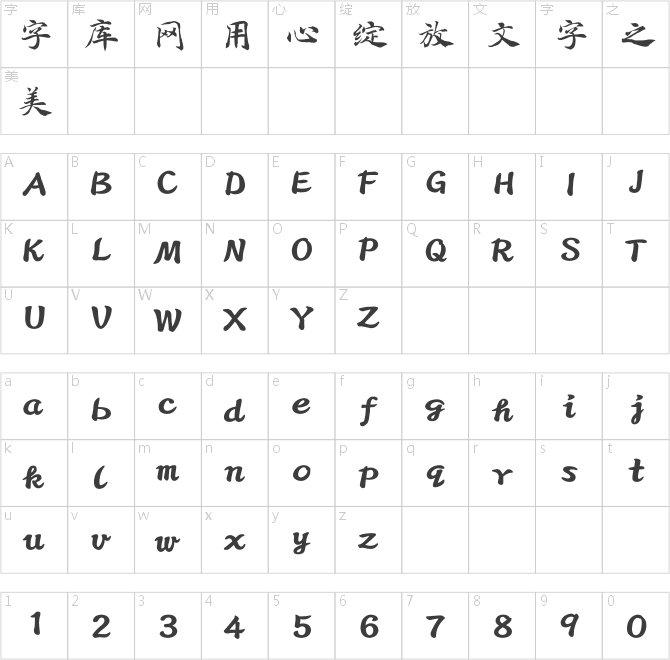
方正字跡-天華褚體 詳情頁(yè)
字體名稱: 方正字跡-天華
方正字跡-天華褚體
方正字跡-天華褚體字體字庫(kù)是一款讓人賞心悅目、百看不厭的中文字體,適合各類廣告和產(chǎn)品包裝設(shè)計(jì)應(yīng)用,字體大小17.59MB,格式為ttf字體,上傳用戶是趙家玉,作者/版權(quán)方為方正